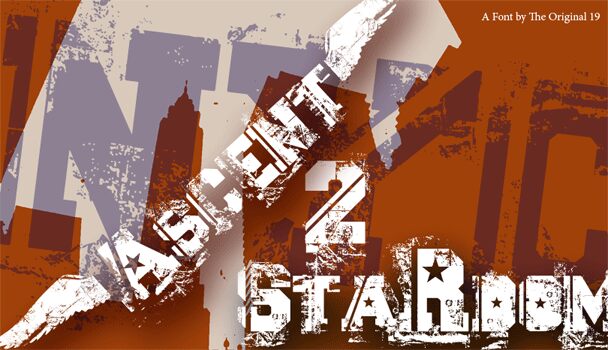
Ascent 2 Stardom di BGizzle Fonts è un font display grunge gratuito con un look vissuto, come strappato da un poster e preso dalla segnaletica stradale usurata. Le maiuscole sono dense e pesanti, frammentate da un’evidente erosione, schizzi e spazi vuoti grezzi, con una stella incisa nella «A» che conferisce all’intero set un’attitudine urbana e decisa.
Si adatta perfettamente a flyer musicali, grafiche skate e streetwear, copertine di mixtape, titoli e branding audace dove il font deve mantenere una texture cruda e danneggiata senza effetti aggiuntivi. Usalo per titoli brevi, esperimenti con loghi o iniziali in stile monogramma quando vuoi che siano le lettere stesse a sporcarsi le mani.